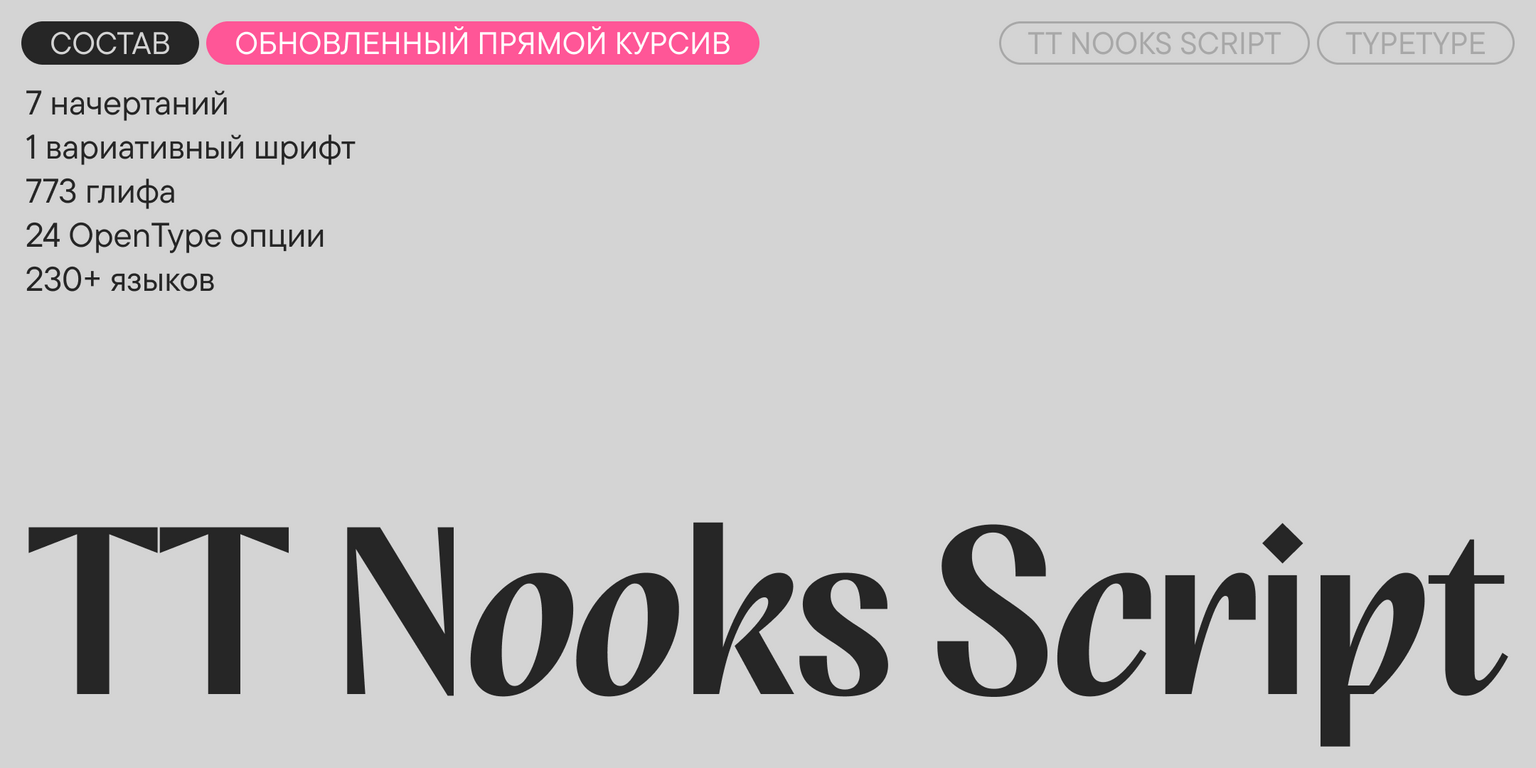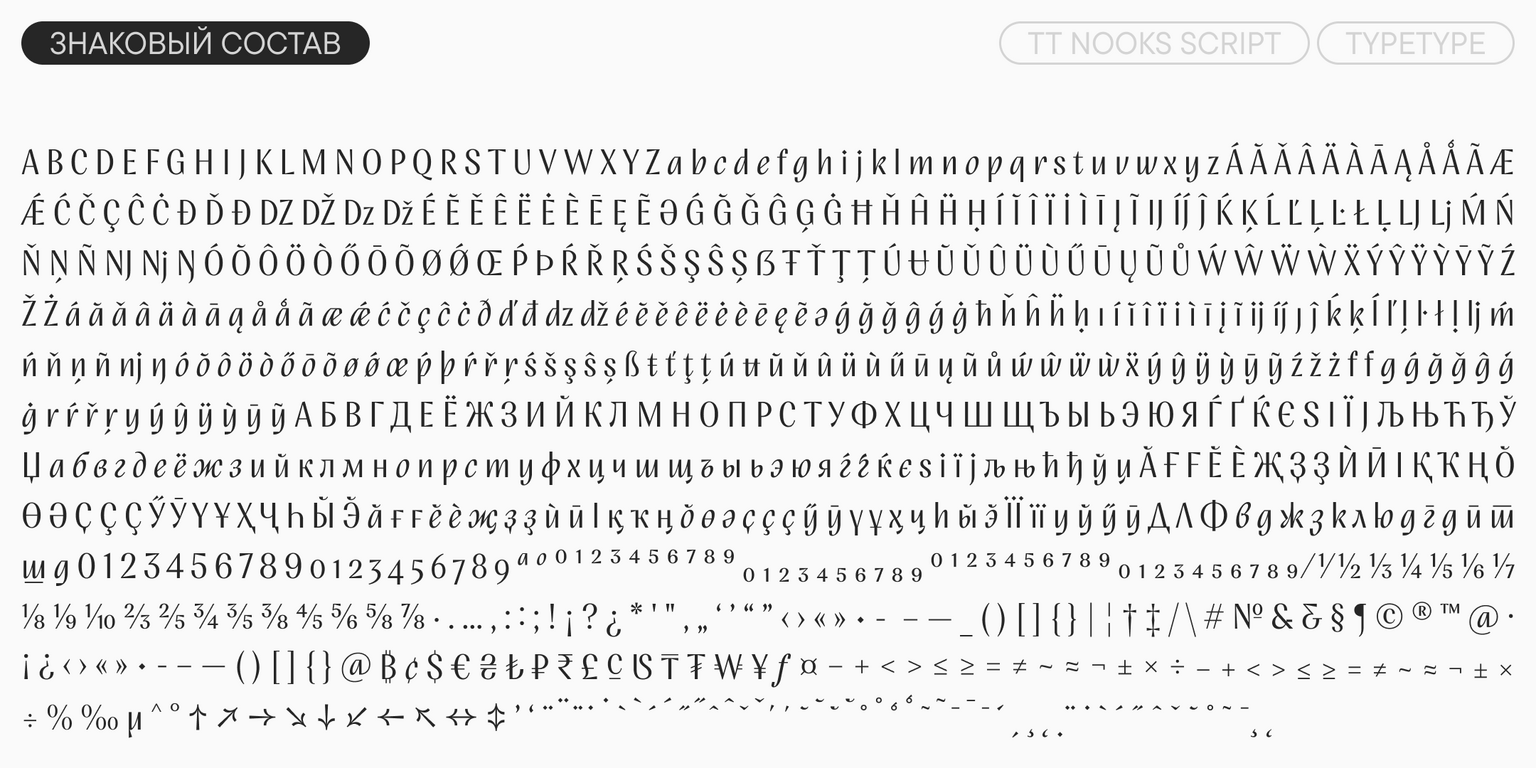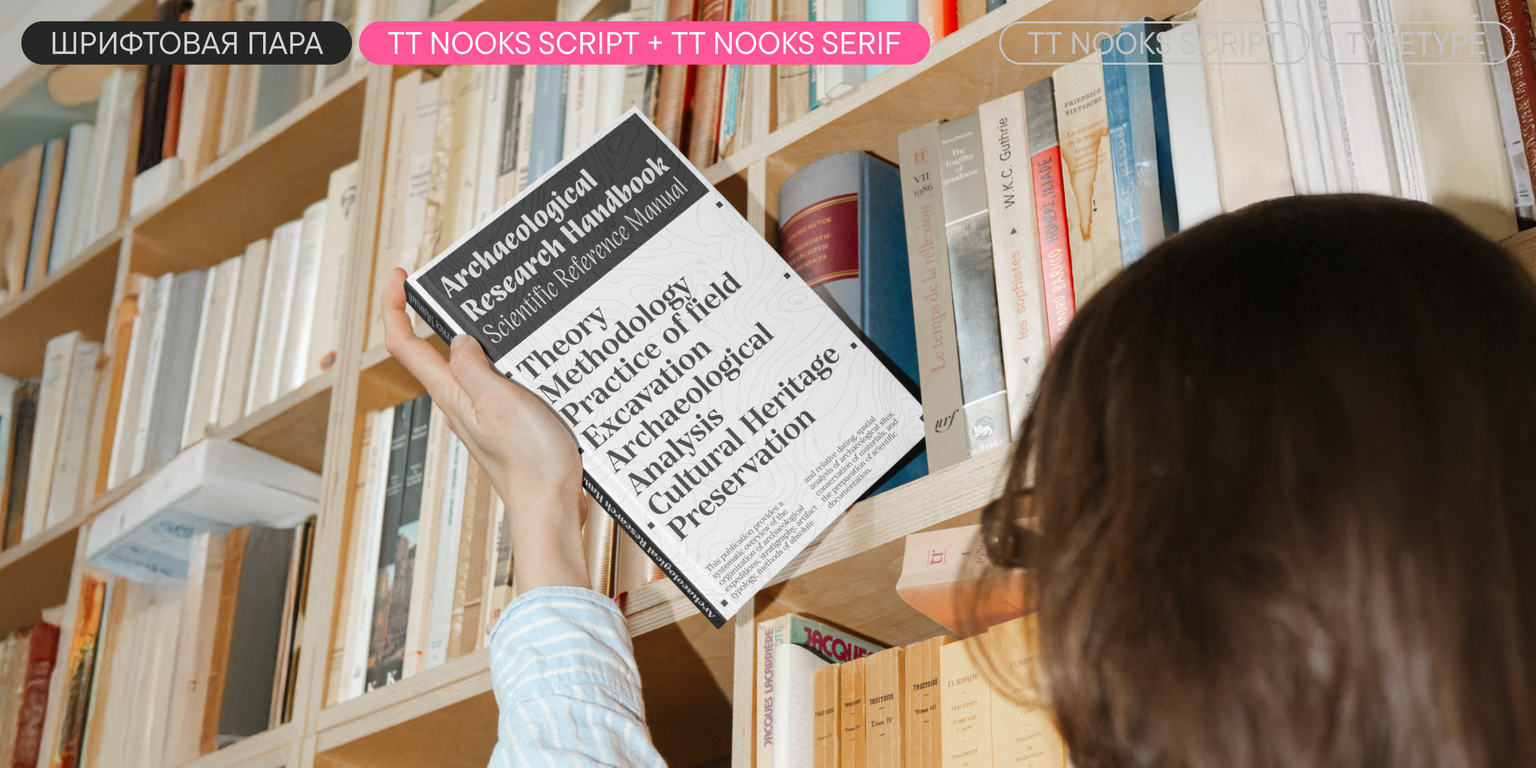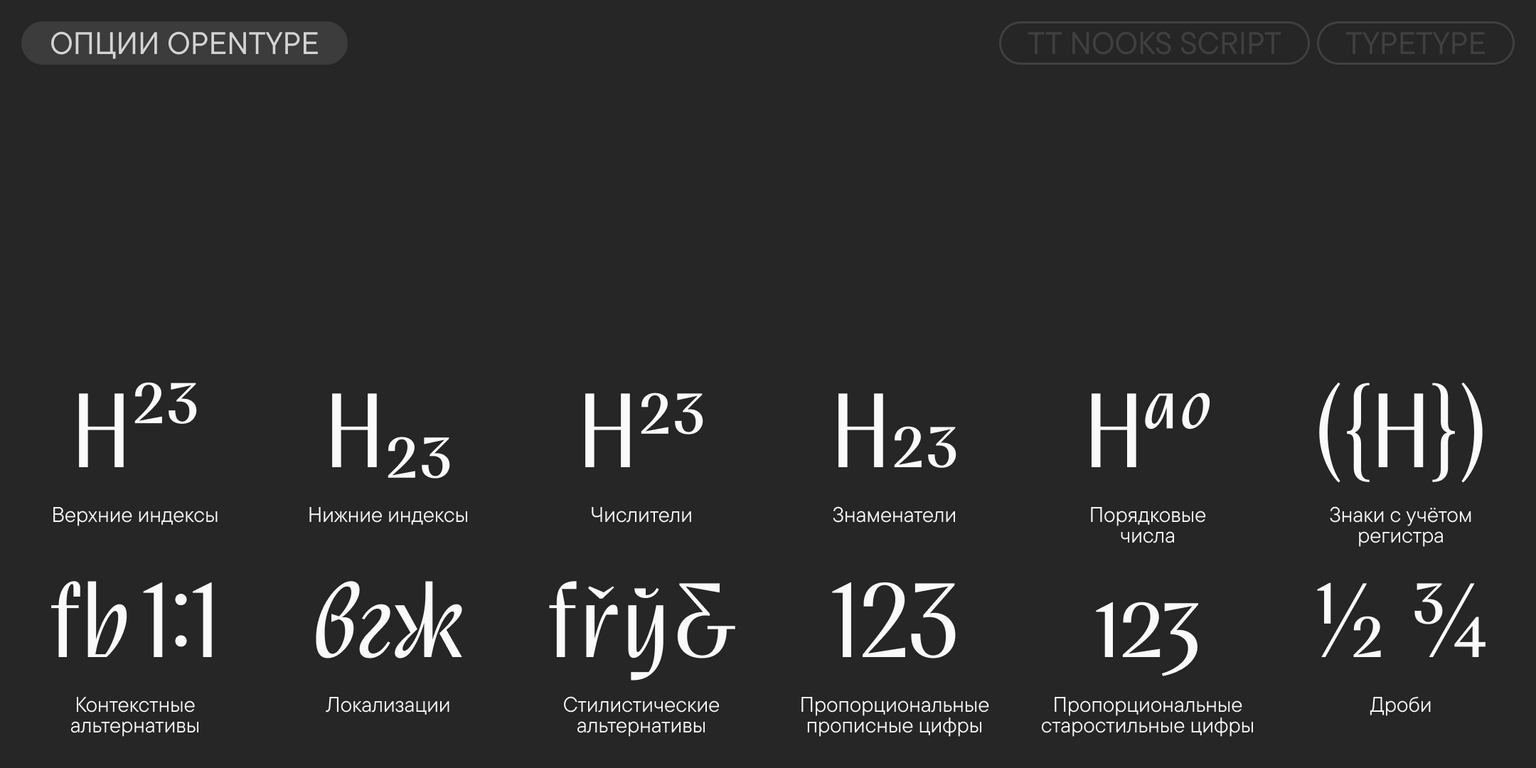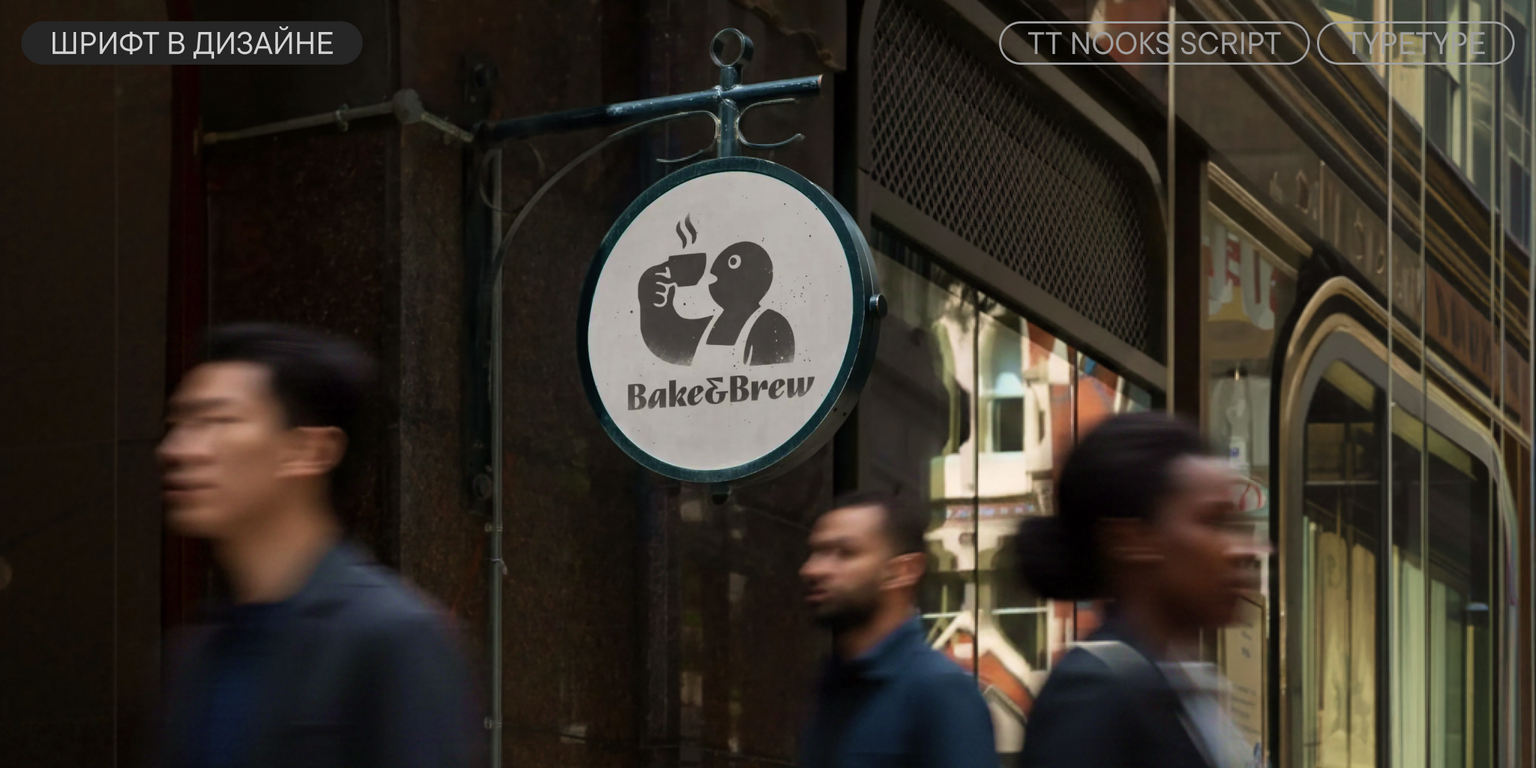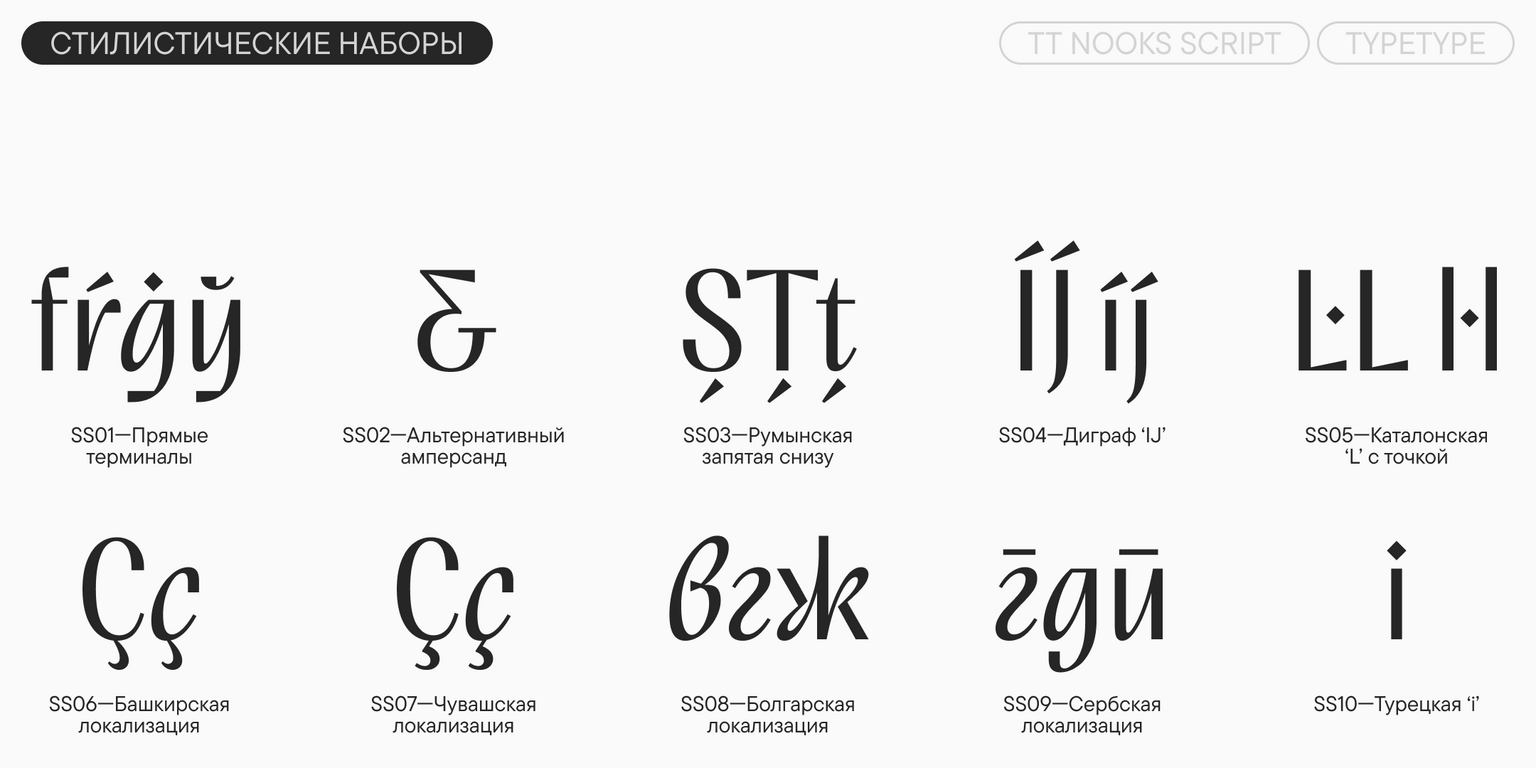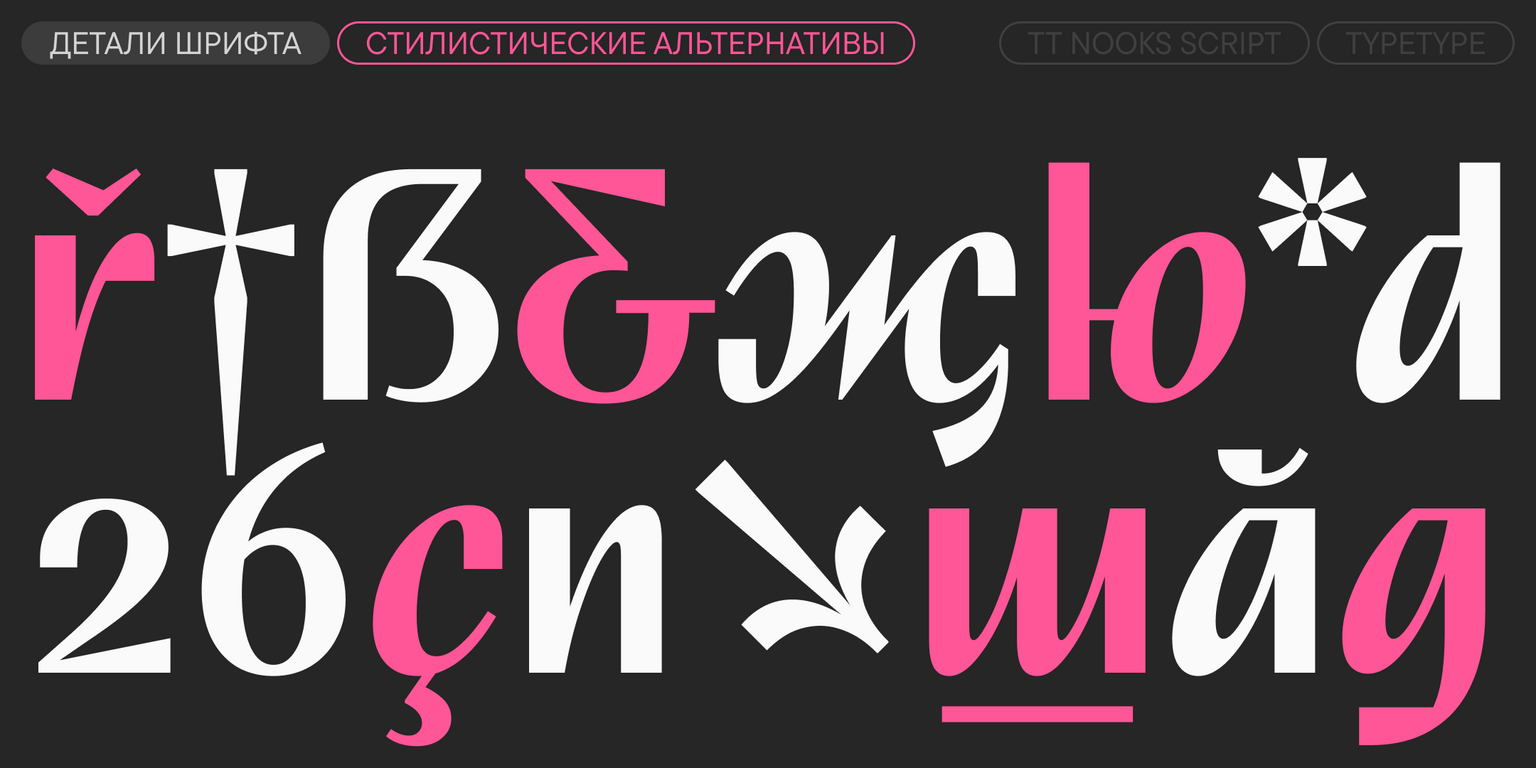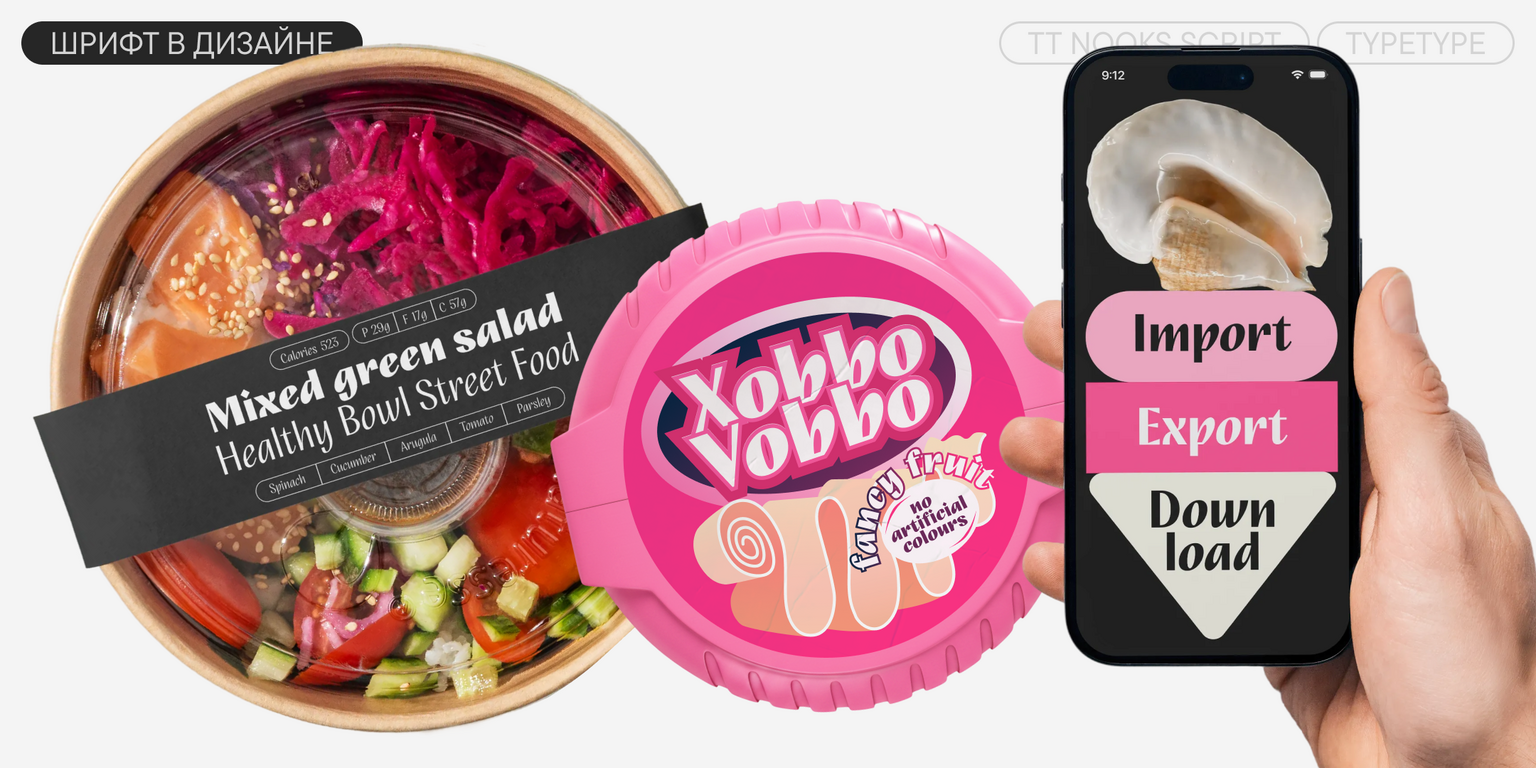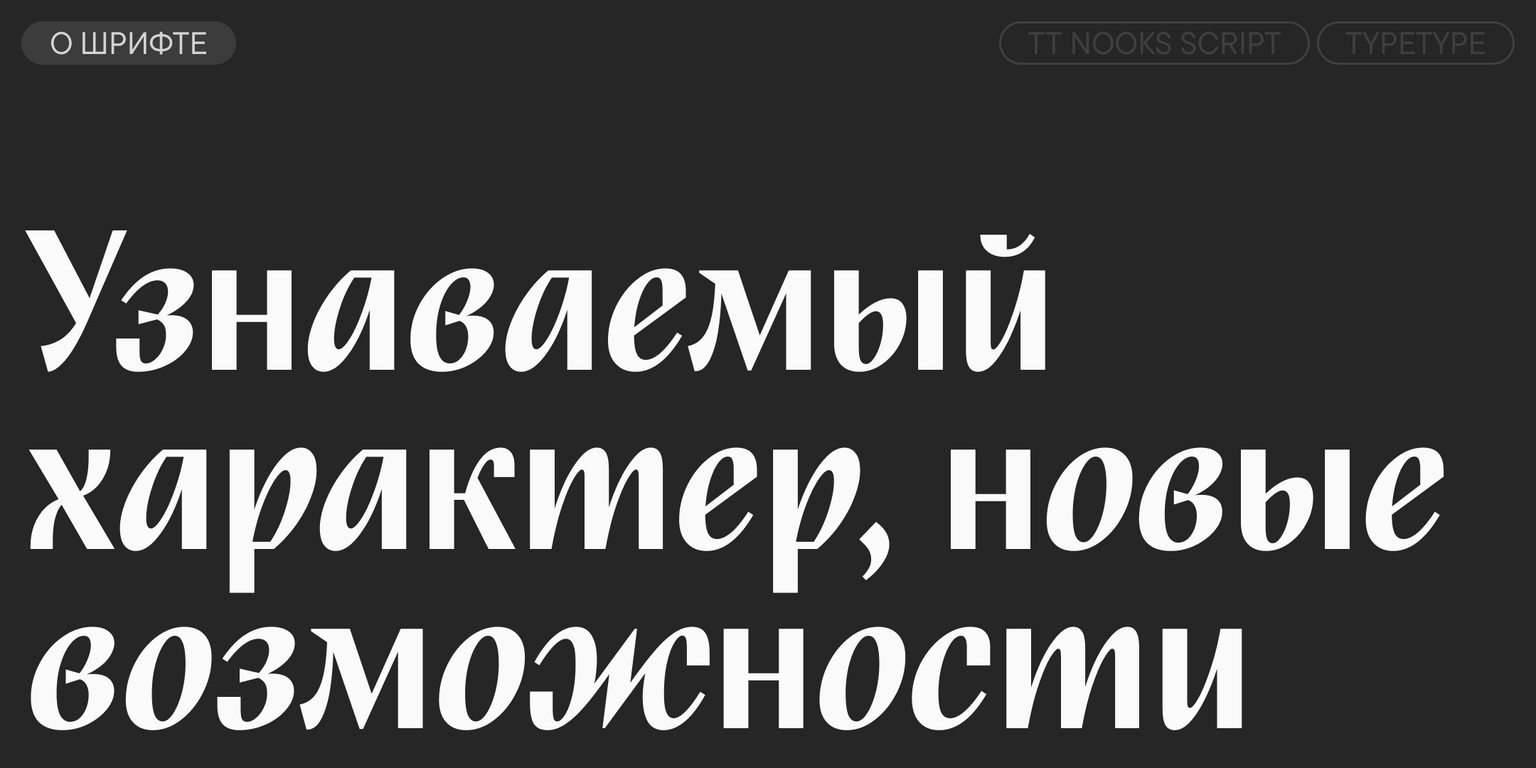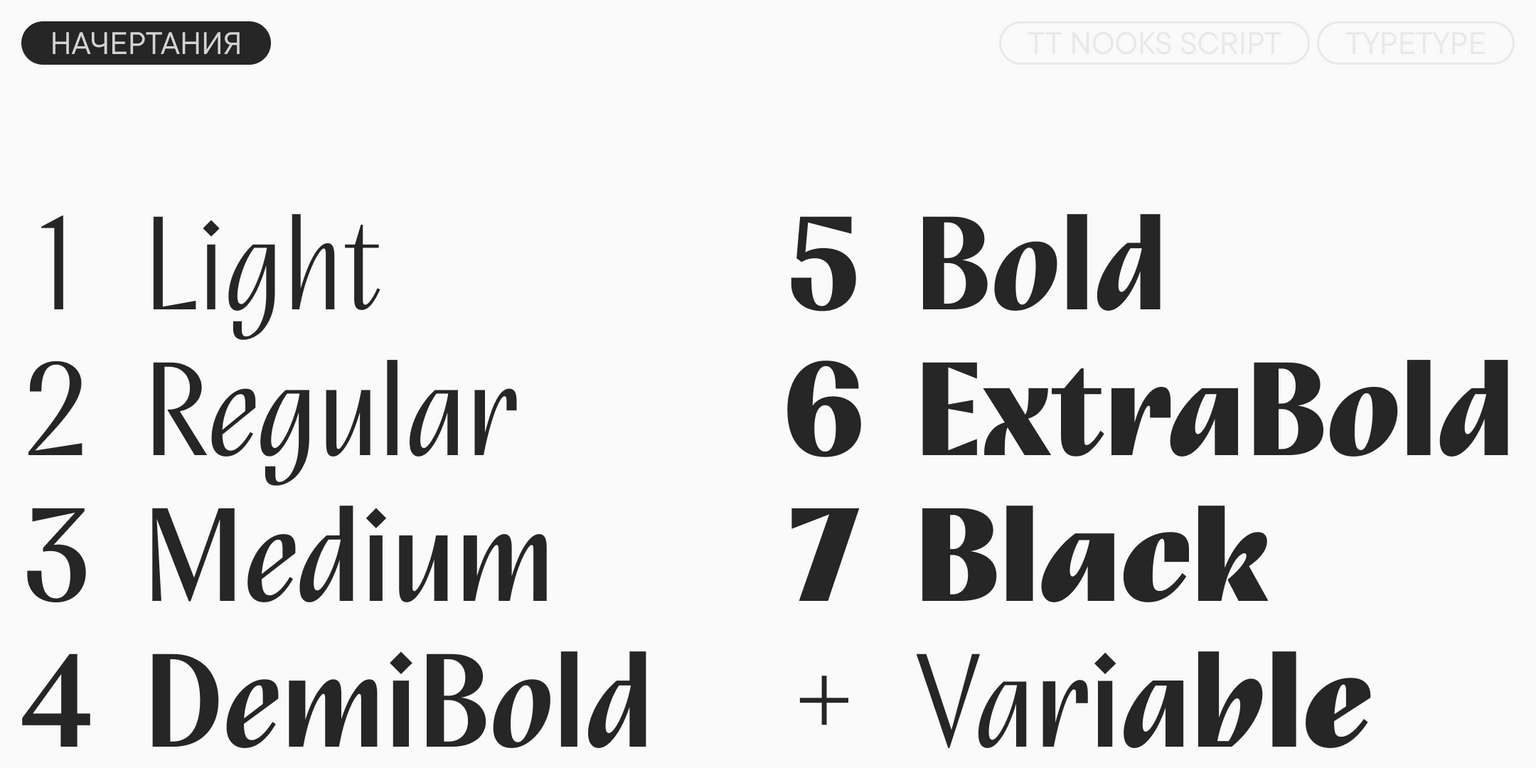
TT Nooks Script
TT Nooks Script — ТТ Нукс Скрипт
Произносится «ТТ Нукс Скрипт». «Nooks» — производное слово от nook, в переводе с английского «закоулок». «Script» произносится как «скрипт», в переводе с английского «курсив». Буквы «TT» являются аббревиатурой названия компании.
TT Nooks Script — прямой курсив с отсылкой к каллиграфической традиции, построенный по всем принципам письма ширококонечным пером. У него узкие пропорции, яркий контраст и выразительный характер.
TT Nooks Script — прямой курсив, нарисованный ширококонечным пером
Если бы TT Nooks Script был человеком, то его можно было описать как элегантную даму с независимым и твёрдым характером — утончённую, но с внутренним стержнем. Шрифтовая гарнитура уникальна и не имеет прямых аналогов: это прямой курсив, построенный по всем классическим принципам письма широким пером. В основе формы букв — естественные приёмы каллиграфа: плавные переходы от толстого штриха к тонкому, характерные соединения и уникальный ритм строки. Изначально гарнитура вышла в 2018 году и включала в себя всего 4 начертания. Спустя 8 лет мы её значительно преобразили: переосмыслили формы букв, пересмотрели пропорции. Для удобства использования гарнитуры мы пересчитали толщины всех начертаний и добавили ещё три новых начертания. При этом общее впечатление и образ шрифта остались прежними: TT Nooks Script по-прежнему аутентичен, благороден и легко узнаваем. Также гарнитура получила вариативную версию, которая позволяет плавно регулировать толщину штриха в широком диапазоне, а также полностью новое техническое наполнение.
TT Nooks Script это 8 начертаний, включающих вариативную версию
О гарнитуре TT Nooks Script
Встречайте TT Nooks Script версии 2.000! Значительно обновили шрифт: переработали графику букв, сохранив оригинальную идею, увеличили кассовый состав, добавили новые функции, альтернативные знаки и языки.
TT Nooks Script — шрифт с уникальным рисунком, который не имеет прямых аналогов. Это прямой курсив с отсылкой к каллиграфической традиции, построенный по всем принципам письма ширококонечным пером. У него узкие пропорции, яркий контраст и выразительный характер. Изначально шрифт был частью экспериментального семейства TT Nooks. Теперь TT Nooks Script и TT Nooks Serif переросли в две самостоятельные гарнитуры, которые по-прежнему умеют работать в паре.
Прописные знаки выглядят более статично, у них колкий характер благодаря острым деталям. Формы строчных ближе к «классическому» курсиву: они выглядят динамично, при этом мягко и округло. Также набор выглядит по-разному в кириллице и латинице: в кириллице больше интересных деталей, а латиница выглядит спокойнее. Настроение между начертаниями тоже меняется: в тонких проявляются гуманистические черты и артефакты, свойственные непрерывному движению плоского пера. В жирных набор становится очень плотным, а ритм — динамичным.
Среди отличительных особенностей шрифта — необычные формы полуовалов и арки. Терминалы ряда знаков очень закруглённые и крупные. Есть каллиграфические формы. Диагональные штрихи и перекладины немного «расклешённые», что особенно заметно в прописных знаках. Пунктуация и диакритика крупная и ромбовидная. Все эти детали подчёркивают уникальный авторский рисунок TT Nooks Script, в котором каллиграфические принципы смешиваются с дизайнерскими приёмами.
В обновлённую версию мы добавили четыре новых начертания, в том числе вариативное, и серьёзно расширили кассовый состав: дополнили расширенную кириллицу и латиницу, развили основной набор валют (появились биткоин, лира, рупия, сом, сум, тенге, тугрик, вон), добавили дроби и служебные знаки. Также в гарнитуре появились новые OpenType опции, языки и стилистические наборы (например, с прямыми терминалами, которые особенно ярко раскрываются в жирных начертаниях).
TT Nooks Script — дисплейный шрифт, который ярче всего раскрывается в крупном и среднем размерах. Он подойдёт для разных задач: оформления упаковки, обложек книг и журналов, плакатов и афиш, брендинга и использования в вебе.
В TT Nooks Script 2.000 входит:
• 8 начертаний: 7 прямых и 1 вариативный шрифт;
• 773 знака в каждом начертании;
• 24 OpenType опции;
• 10 стилистических наборов;
• 230+ языков.
Анна Кондрашова
Антонина Самохина
Что изменилось в шрифте:
• Количество начертаний выросло с 4 до 8, в том числе появилось вариативное;
• Количество знаков выросло с 677 до 773: в частности, мы дополнили расширенную кириллицу и латиницу, расширили основной набор валют (биткоин, лира, рупия, сом, сум, тенге, тугрик, вон), добавили дроби и служебные знаки;
• Появились новые стилистические сеты — в том числе ss01 с прямыми терминалами, которые особенно ярко раскрываются в жирных начертаниях;